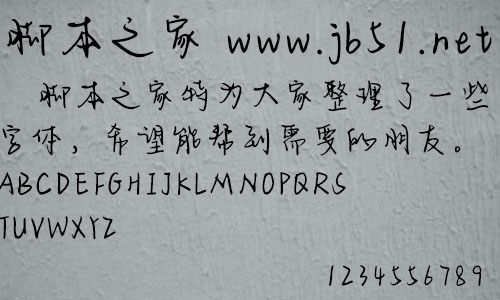
Aa追風(fēng)少年的天空一款不錯(cuò)的藝術(shù)字體,由Aa字庫出品,字體筆觸適中,字形流暢灑脫,適合應(yīng)用于藝術(shù)設(shè)計(jì)、平面宣傳設(shè)計(jì)、網(wǎng)頁設(shè)計(jì),書法字帖等領(lǐng)域,需要的朋友可以前來本站下載。